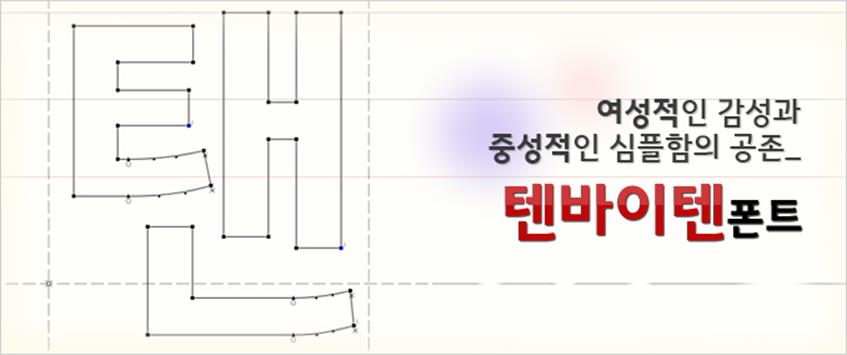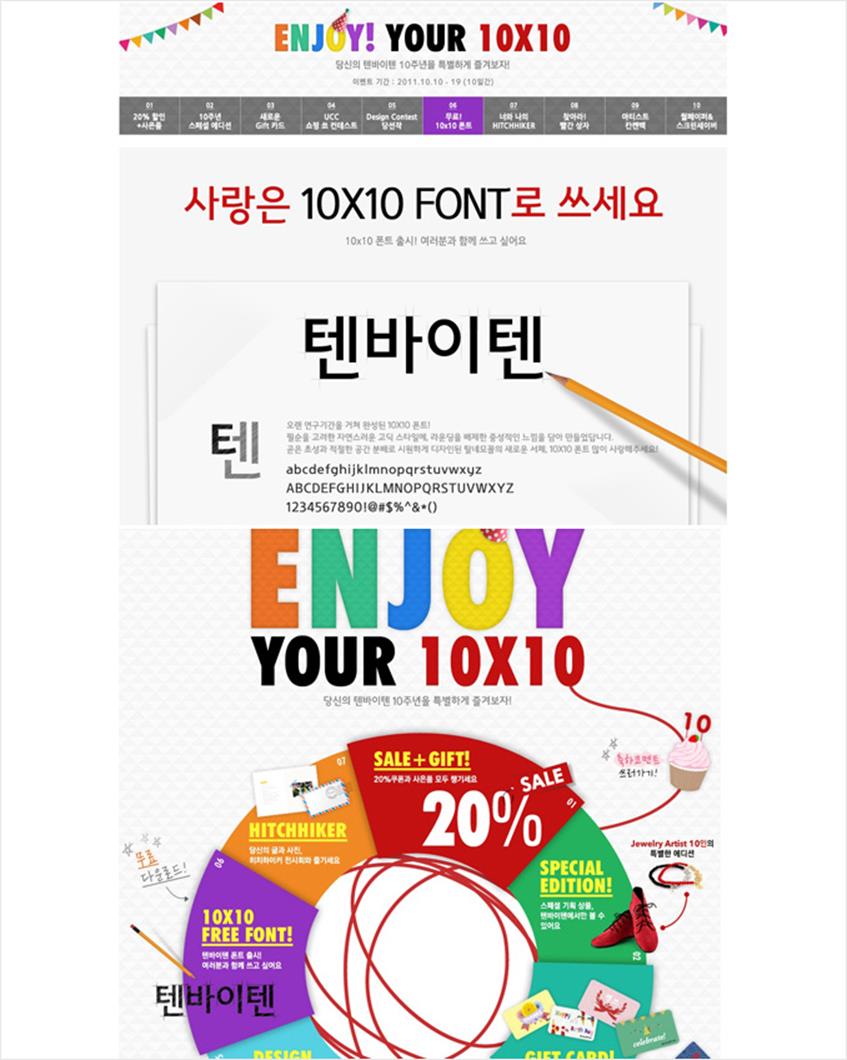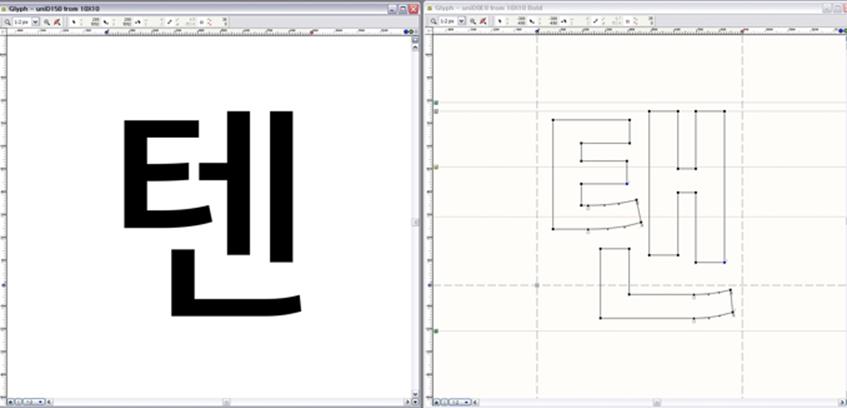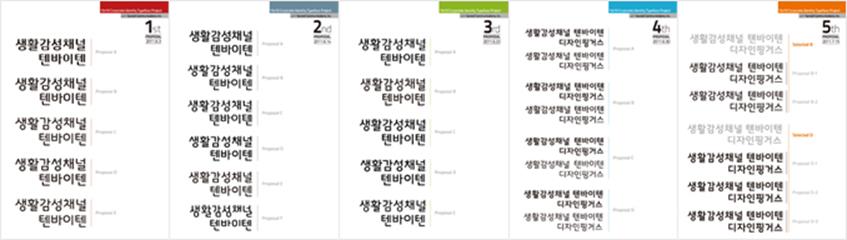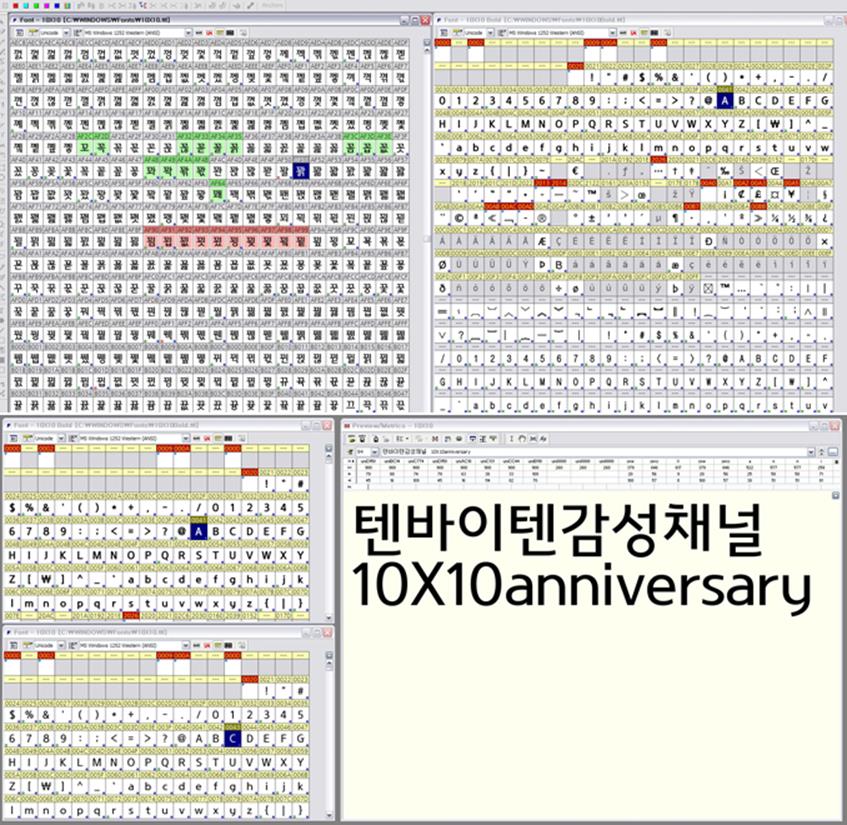
여성적인 감성과 중성적인 심플함의 공존_텐바이텐 폰트
텐바이텐 폰트 제작 프로젝트는 창립 10주년을 맞은 텐바이텐(www.10×10.co.kr)이 지난 2011년 10월 10일, 열 번째 생일을 맞아 고객에게 즐거움과 새로움을 주고 신뢰 받는 기업 목표를 기반으로 그 동안 받은 사랑을 보답하기 위해 개발된 무료 폰트이다. 텐바이텐과 산돌커뮤니케이션이 MOU를 맺고 오랜 연구 끝에 완성한 10X10 폰트는 필순을 고려한 자연스러운 고딕 스타일에 라운딩을 배제한 중성적인 느낌을 담아 디자인되었다. 곧은 초성과 적절한 공간 분배로 시원하게 디자인해 탈네모꼴의 새로운 서체 스타일을 선보이고자 했다.
텐바이텐 10주년 이벤트 페이지
텐바이텐 폰트는 산돌의 여러 디자이너와 연구원이 머리를 맞대고, 두 달 정도의 시안작업을 거쳐 텐바이텐 담당자와 7번 이상 의견을 조율해 가며 10월 10일 이벤트 일정에 맞춰 프로젝트를 진행했다. 다양성을 위해 실험적인 폰트 디자인을 제안하는 등 여러 시안을 준비하기 위해 생각보다 시안 결정 과정에 오랜 시간 집중해야 했지만, 결과적으로 텐바이텐만의 개성을 살리는 동시에 견고한 고딕 형태의 디자인으로 다듬어진 만족스러운 시안으로 결정되어 본격적인 폰트 제작이 이루어졌다.
다른 기업 전용 서체와 차별화되는 텐바이텐 폰트만의 특징은 필순을 고려한 자연스러운 고딕 스타일에 라운딩을 배제한 중성적인 느낌을 담은 폰트라는 점이다. 곧은 초성과 적절한 공간 분배로 시원하게 디자인된 탈네모꼴의 새로운 서체인 셈이다. 또한, 자소 ‘ㄴ’, ‘ㄹ’, ‘ㄷ’, ‘ㅍ’, ‘ㅌ’과 ‘ㅊ’, ‘ㅎ’의 상투에 미려한 곡선을 넣어 부드러움과 견고함이 공존할 수 있게 디자인했다. 한글뿐만 아니라 텐바이텐에서는 숫자와 영문을 굉장히 많이 사용하고 있어 한글 못지 않은 비중을 두고 작업해야 했다. 전체적인 컨셉은 한글에 맞춰 가장 어울리는 영문을 만드는 것이었고 톡톡 튀는 감성적인 텐바이텐의 이미지에 맞게 세련되면서도 심플한 라틴 알파벳 서체를 디자인했다.
텐바이텐에 제안했던 여러 시안들
텐바이텐 폰트를 만들 때 가장 고민스러웠고 중요하게 생각했던 부분은 폰트의 ‘색’이었다. 현대카드 전용 서체를 비롯해 CJ제일제당 패키지 전용 서체와 조선일보, 중앙일보 전용 서체 등 수많은 기업전용 폰트들이 나와 있었고, 기존 폰트와는 차별화 되면서 텐바이텐만의 색깔을 강조하는 폰트를 만드는 것이 중요했다. 그래서 나눔고딕처럼 여성스럽고 대중적인 고딕이 아닌 중성적인 고딕 형태의 폰트를 개발하기로 한 것이다. 미세하지만 기존의 고딕과는 확연하게 차별화된 디자인이다.
텐바이텐 폰트는 한글 2,350자와 약물, 영문은 폰트랩과 아시아폰트스튜디오를 이용해 디자인하고,
한글 8,822자는 드리거(폰트메이커)에서 작업을 진행했다.
지난 5년 동안 폰트디자이너로 일해 오면서 팬시폰트나 신서체(마스카라체) 위주의 작업을 해오다 처음으로 텐바이텐을 위한 기업전용 서체를 만들게 되어 개인적으로 의미 있는 프로젝트였다. OEM이라는 부담감과 서포터 역할이 아닌 PM이라는 역할을 처음 수행하면서 ‘내가 잘 할 수 있을까?’라는 걱정이 앞서기도 했다. 하지만 내 디자인이 기업 전용 서체로 많은 이들에게 선보일 수 있다는 설렘에 힘을 얻어, 책임감을 갖고 작업에 임할 수 있었다. 애착이 많이 가면서도 아쉬움이 많이 남는 프로젝트였지만 새로운 도전이었고 다양하게 쌓은 노력들이 잘 표현된 것 같다. 무료로 제공되고 있는 폰트인 만큼 많은 사람들이 사용해 주고 사랑을 받았으면 하는 바람이다.